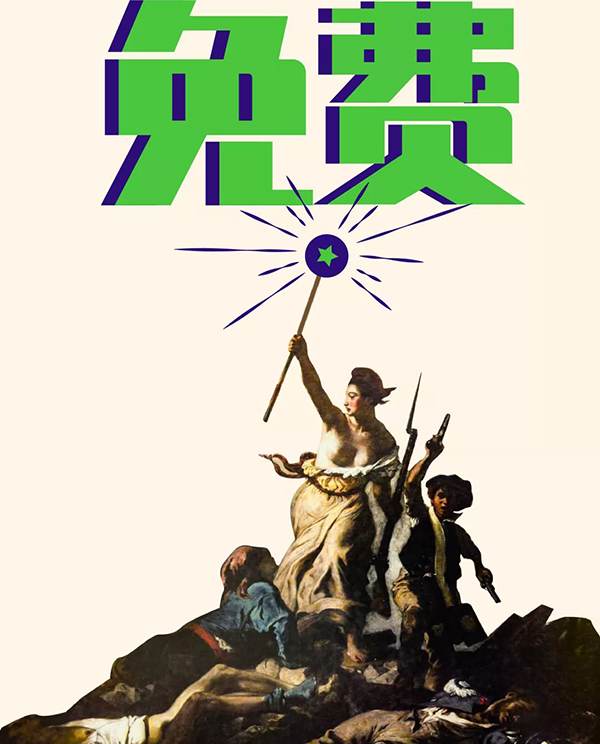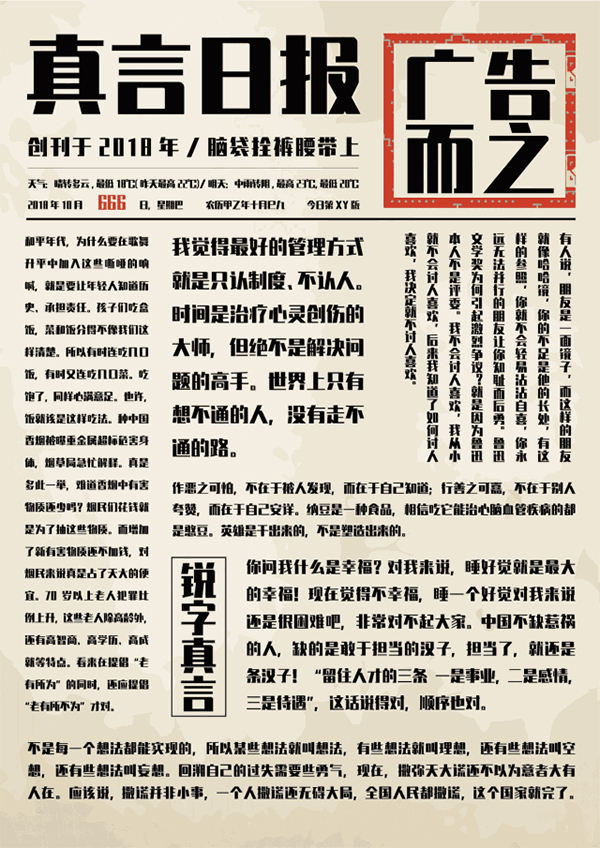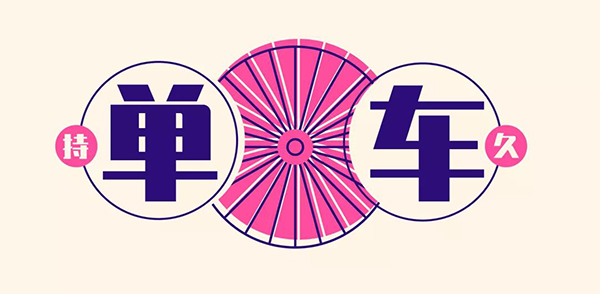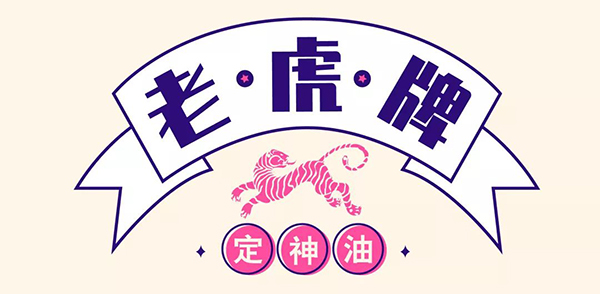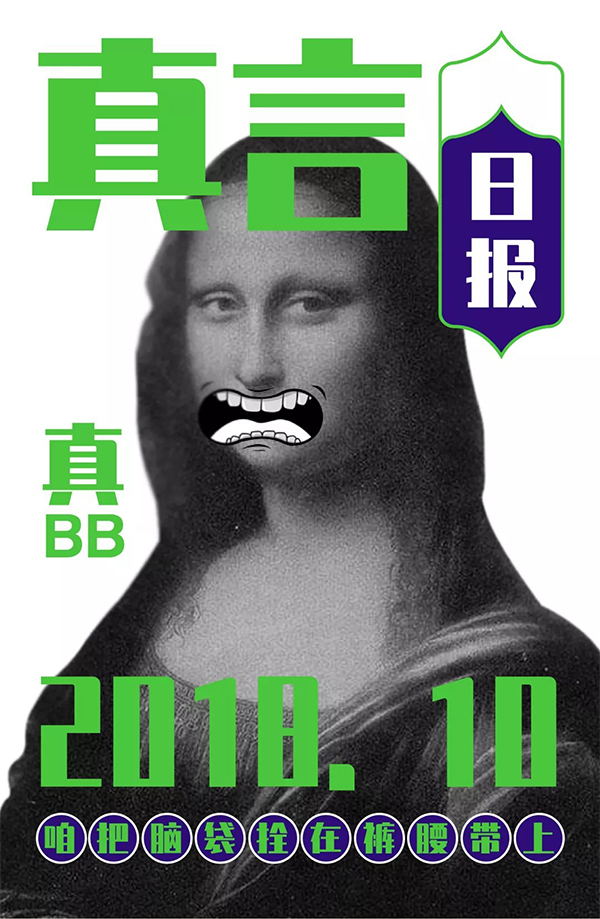
实话实说讲真事,真心真言出真字!
锐字真言体
哪个“真”?
“真”坦诚
“真”创新
“真”有才
讲真!“真言体”是十足的“真”
真言体笔触浑厚有力,笔画曲折有度,字形个性鲜明,刚柔并济,落笔简洁有序,给人以遒劲有力、端正凝练的感受。直角与圆角的错落搭配使得字体婉转有度,落落大方,具有自己独到的风格!
这款字体特别适用于文字标题、竞技视觉、广告设计、个性品牌设计推广、企业宣传及时尚品牌的设计应用。